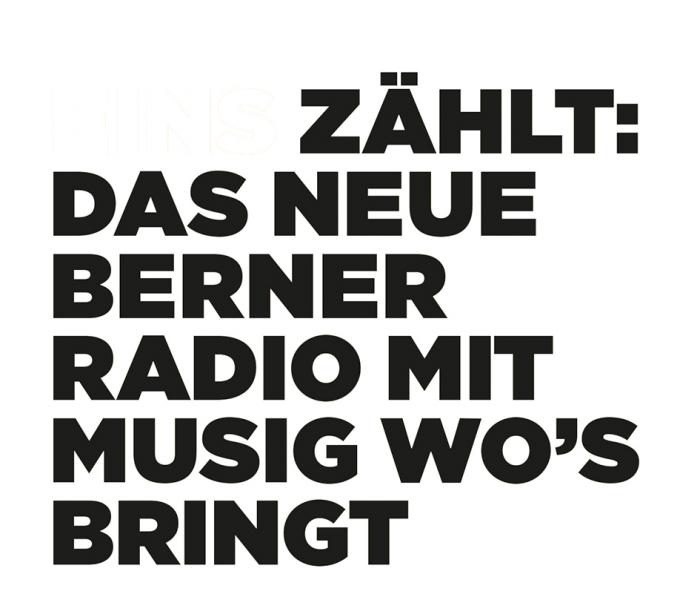
Bevor ich Radio Bern anrufe - kennt jemand von euch diese Schrift?
Für Print und vorgerenderten Online-Text verwendet Radio Bern1 die Gotham in verschiedenen Schnitten, im www mischen sie für den Text die Proxima Nova dazu. Fällt offensichtlich keinem auf ;-)
Ja in der Versalschreibung gibt es bei der Proxima Nova viele Ähnlichkeiten zur Gotham und nur wenige augenfällige Unterschiede: runde 3, runde Punktierungen, Mittelspitze vom M ragt bis zur Grundlinie, …
Weil Proxima Nova aber im Vergleich deutlich günstiger zu haben ist, gilt sie als gern genommene Gotham-Alternative. Ihr Schriftbild (gemischter Mengensatz) ist aber leider bei weitem nicht so schön ruhig und ausgeglichen.  :-(
Am Preis wird das vermutlich nicht liegen, weil ja beide Fonts zum Einsatz kommen. Ich vermute eher, dass die Mischung durch die Verfügbarkeit begründet ist – die Gotham ist erst seit Juli als webfont erhältlich. Design und technische Umsetzung dürften jedoch wesentlich vor Juli 2013 begonnen worden sein.
Das kommt noch hinzu. Ich hatte das allgemein formuliert und nicht unmittelbar auf den Sender bezogen. Aber wenn ich mich nicht irre, ist selbst diese Weblizenz eben auch teurer. Und man kommt umständlicher ran.
So wie es aussieht, macht man das Gotham-Rendering bei Radio Bern mit der »Printlizenz« und hat sich bei dem dynamischen Part – sicherlich erstmal aus Verfügbarkeitsgründen – für die Proxima Nova entschieden. Wir stehen hier gerade vor einer ähnlichen Entscheidung.